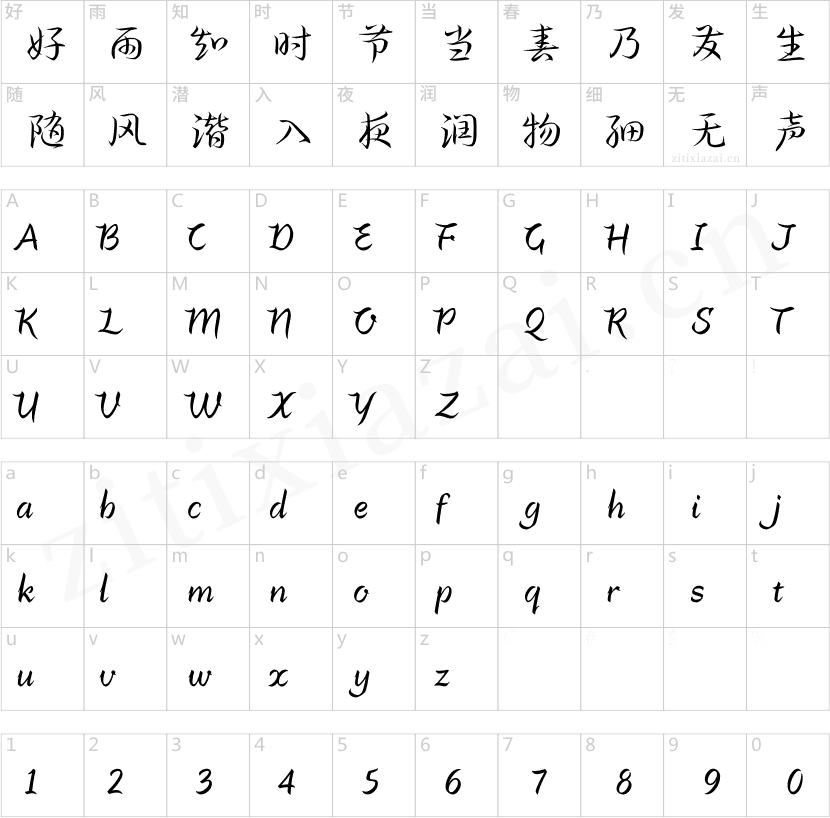
汉仪妙草
汉仪妙草,这款字体结构工整、笔画清晰,兼顾美观与易读性,适用于标题、正文、海报、包装、LOGO 等多种场景。字形优雅稳定,风格百搭耐看,适配日常排版与创意设计,让文字呈现更舒适、更具质感。汉仪妙草一笔一画,皆是细节,以均衡的比例、流畅的线条打造舒适视觉体验,字形端正大气,风格简约现代。无论是商业设计、品牌宣传还是日常排版,都能轻松驾驭,让文字更有格调与力量。汉仪妙草字体下载。
• 字体说明:汉仪妙草这款字是根据现行字库字体的设计标准进行制作的,严格意义上来讲不算作纯粹的草书。在设计中借用了很多草法,但同时也兼有许多行书的处理方式,不管是简繁写法的区分,还是为防止混淆所做的不同部首、部件写法的区分,以及为了兼顾一定识别性所做的写法上的筛选等,都没有完全符合草书的要求。这些也都是为了保证这款字更加符合当代环境下的使用需求所做的必要的取舍。作为一款具有实验性和开创性的字体,汉仪妙草潇洒写意,逸趣横生,颇具草书简约之美,排版工整而富于变化,适合应用于文化艺术场景,如展览海报、书籍画册等。推荐与宋体搭配使用,在增强易读性的同时更能突出汉仪妙草的飘逸。